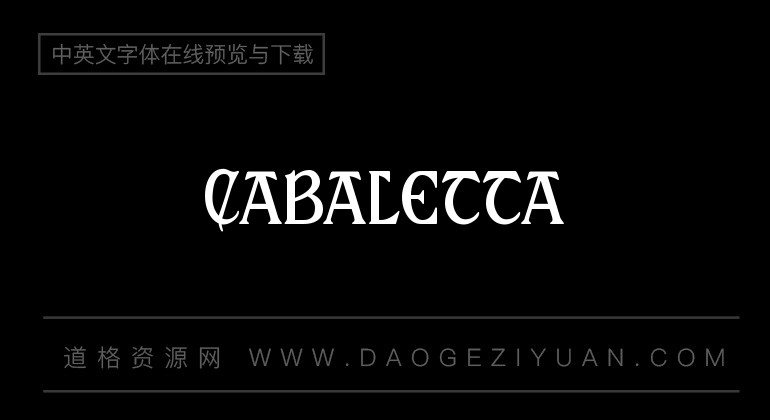
Cabaletta
Cabaletta 是一种手写风格的字体,由美国设计师 Brian J. Bonislawsky 创造。该字体于2017年发布,包含多种粗细程度和变体,可用于多种设计场景。 Cabaletta 字体的特点是其流畅的线条和手写风格,它的字母形状和笔画都带有自然的变化和不规则性。这种写实的手写风格为设计师提供了一种传达人性化和个性化的方式。 Cabaletta 字体适用于多种设计领域,如广告、海报、标志、名片和包装设计。它的多种粗细程度和变体还可以用于标题、副标题和正文等不同的排版需求。此外,该字体还支持多种语言,并包含了各种符号和连字符,以满足不同的排版需求。 总之,Cabaletta 是一种独特的字体,它以其流畅的线条和自然的手写风格,为设计师提供了一种传达个性和人性化的新方式。
Cabaletta是一款非常不错的手写艺术字体,具有很好的视觉感,适合于文化类的宣传设计、商业类品牌的广告和产品包装设计以及个性化文字排版等较多场景。